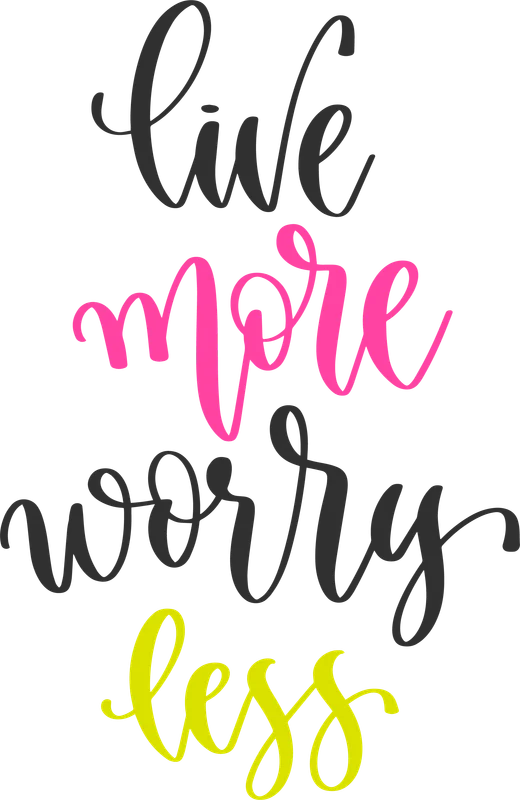
Slogan "Live More Worry Less" font chữ nghệ thuật
Slogan "Live More Worry Less" font chữ nghệ thuật — In hình slogan "Live More Worry Less" với font chữ nghệ thuật độc đáo. Tuyệt vời cho áo thun, túi tote, cốc, sticker. Tạo phong cách sống tích cực.
Trong hình có: chữ viết, slogan
Phong cách: line-art · Cảm giác: cool
Tông màu chủ đạo: xám, hồng, vàng